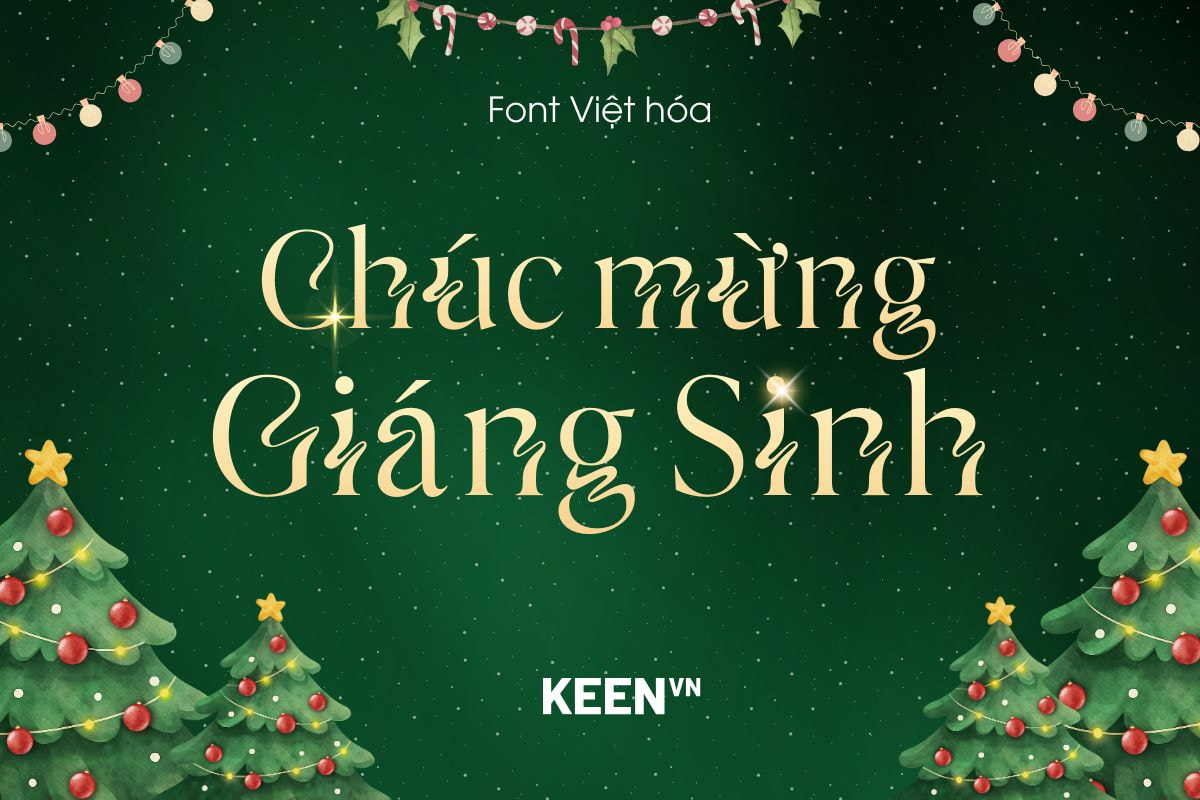
Font Việt hóa TH Zighead mang đến một phong thái táo bạo và sinh động, khiến bất kỳ thiết kế nào cũng trở nên nổi bật ngay lập tức. Được tạo nên từ sự hòa quyện giữa những điểm nhọn sắc bén và các đường cong mềm mại, Zighead khiến từng ký tự như đang chuyển động, tựa một dòng mực uốn lượn đầy nghệ thuật. Đây là kiểu chữ trang trí có chân mang tính cách điệu cao, mang đến cảm giác vừa mạnh mẽ vừa vui tươi – đúng chất “zing” đầy năng lượng mà nhiều nhà thiết kế tìm kiếm.
TH Zighead sở hữu đầy đủ bộ ký tự in hoa và in thường, hỗ trợ hoàn chỉnh chữ Latin tiêu chuẩn, dấu câu và chữ số. Sự đa dạng này giúp font dễ dàng ứng dụng trong nhiều tình huống khác nhau, đặc biệt là những thiết kế cần điểm nhấn thị giác thật mạnh. Mỗi glyph đều mang một hình thái độc đáo, được điều chỉnh tỉ mỉ để tạo nên diện mạo đậm chất thủ công nhưng vẫn sắc nét và hiện đại.
Khi được Việt hóa, Zighead càng trở nên hữu dụng hơn trong các dự án thiết kế dành cho thị trường Việt Nam. Bạn có thể dùng font cho wordmark thương hiệu, poster nghệ thuật, tiêu đề kỹ thuật chữ hay các sản phẩm truyền thông cần sự cá tính và khác biệt. Với TH Zighead, từng câu chữ sẽ trở thành một yếu tố trang trí cuốn hút, giúp tác phẩm của bạn không chỉ đẹp hơn mà còn mang màu sắc riêng biệt, đầy sáng tạo.